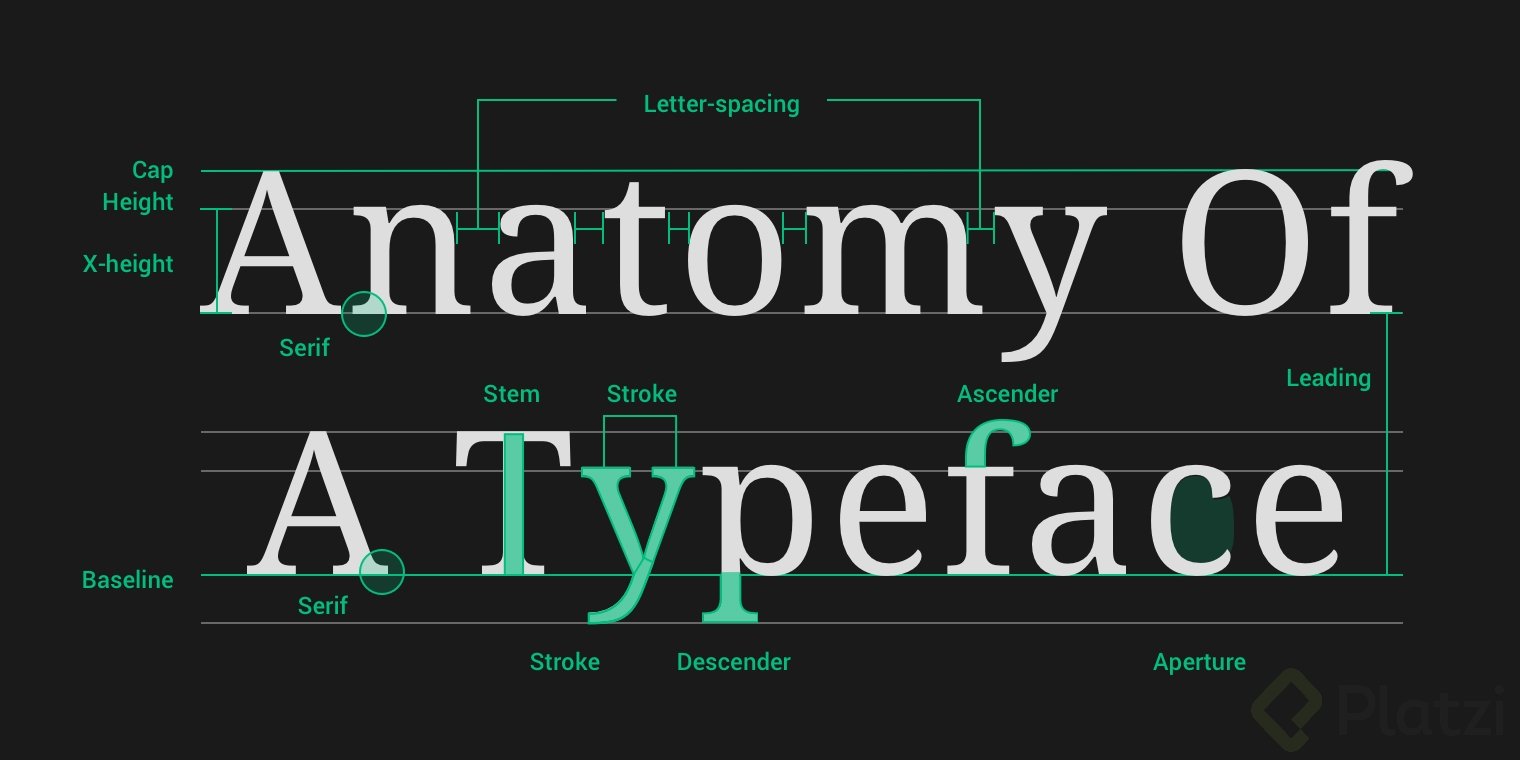
Tipografía: Uso y Contraste en Diseño Gráfico
¿Cómo elegir la tipografía correcta?
La tipografía es un pilar fundamental en el diseño gráfico. Puede ser un reto encontrar la fuente adecuada, ya que es esencial para transmitir un mensaje claro y efectivo. Entender las funciones y los métodos para elegir y utilizar tipografías puede transformar el resultado de tus diseños. Como diseñadores, necesitamos transmitir la información de manera clara; desde detalles de eventos hasta características de productos.
¿Por qué es importante la tipografía?
La tipografía va más allá de seleccionar una fuente estilística; tiene un rol crucial en la comunicación. Aquí hay algunas razones clave por las cuales es importante:
• Transmisión del mensaje: La tipografía no solo transmite un mensaje sino que lo hace de manera literaria y estética.
• Claridad: Facilita que el receptor entienda toda la información sin confusiones.
Al ejemplo de la publicidad deportiva se le puede atribuir una tipografía clara y directa. Usan la tipografía Futura, acompañada de un mensaje breve pero contundente. La combinación con otros elementos como el logotipo o una imagen bien balanceada, asegura que el mensaje llegue adecuadamente al público.
¿Cómo jugar con la tipografía en el diseño?
Existen miles de ejercicios para trabajar la tipografía en el diseño. Estos te permiten explorar combinaciones de color e imagen que refuercen el mensaje. Algunos enfoques incluyen:
• Minimalismo: Mantener el diseño simple evita distracciones y enfoca la atención en lo esencial.
• Creatividad en fotografía: La tipografía y la imagen pueden entrelazarse para acentuar el mensaje. Un buen ejemplo es utilizar tipografía al frente o atrás de elementos visuales en la fotografía para una mayor dinámica.
Además, en piezas gráficas, jugando con la centralización y el alineamiento de la tipografía, se potencia la legibilidad y el impacto visual. Este tipo de disposición, además de lograr equilibrio, permite integrar al protagonista sin que el texto resulte invasivo.
¿Cuáles son las claves para el contraste tipográfico?
El contraste es una herramienta crucial en tipografía para resaltar elementos específicos. Aquí se presentan los cuatro tipos de contrastes más usados:
1. Contraste de peso: Puedes usar tanto tipografías delgadas como gruesas para indicar diferentes niveles de importancia o énfasis en ciertas palabras.
2. Contraste de color: Cambiar el color de ciertos renglones o palabras puede hacer que un mensaje destaque más. Esto es particularmente eficaz en piezas gráficas coloridas.
3. Contraste de tipo: Combina diferentes tipografías que se complementen para crear un efecto visual llamativo. Cada tipografía transmite su propio mensaje; algunas son serias mientras otras pueden parecer más casuales.
4. Contraste de tamaño: Cambiar el tamaño del texto es una técnica directa para enfatizar ideas clave. Se puede agrandar palabras o frases específicas dentro de un diseño, lo que es ideal para captar la atención del lector.
¿Cómo aplicar tipografía en diseños modernos?
Para los diseños modernos, la tipografía debe ser tanto complementaria como funcional. Un enfoque actual implica la integración de la tipografía con fotografías grandes, utilizando espacios en blanco efectivos y evitando elementos distractores, lo cual puede invitar a los espectadores a enfocarse en el producto o el mensaje sin abstracciones innecesarias.
Empleando la creatividad y práctica continua, podrás dominar técnicas tipográficas para satisfacer las demandas de proyectos diversos, desde publicidad deportiva hasta composiciones artísticas más complejas. Adquirir estos conocimientos te permitirá elegir y aplicar las tipografías adecuadas en cualquier diseño.